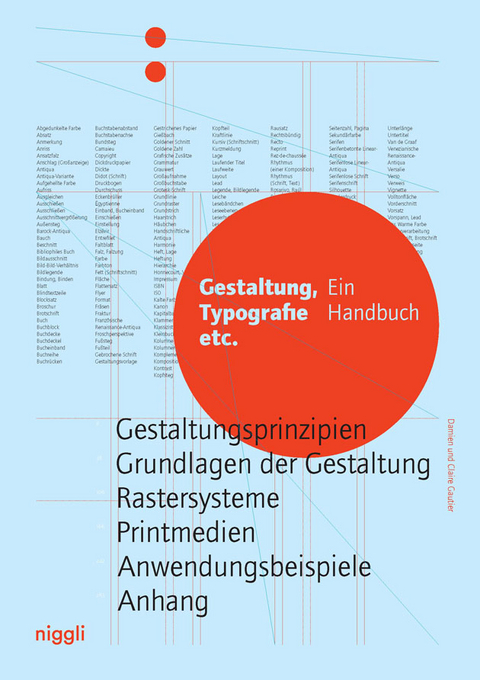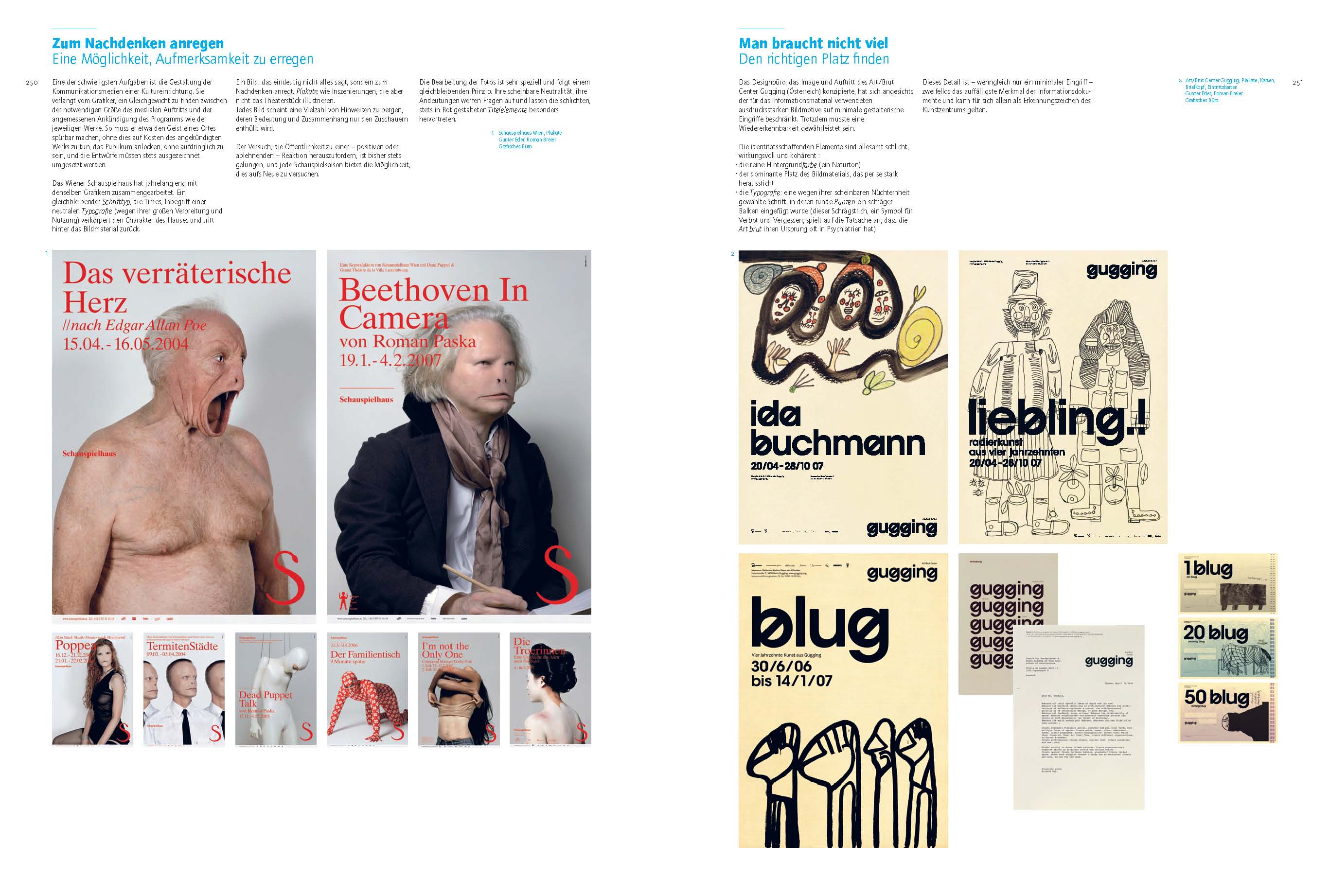
Gestaltung, Typografie etc.
Ein Handbuch
Warum sieht eine Zeitung anders aus als eine Zeitschrift oder ein Buch? Welche Auswirkungen hat die Verwendung einer bestimmten Schrift, welche die eines bestimmten Rasters? Und warum wirkt das eine Layout ausgesprochen passend und überzeugt und ein anderes eindeutig falsch?
Mittels Abbildungen, Zeichnungen und erläuternden Texten werden in diesem umfassenden Handbuch und Nachschlagewerk sämtliche Grundlagen und Fachbegriffe erklärt, deren Kenntnis an der Schnittstelle von Gestaltung und Produktion von Printmedien unumgänglich ist. Vom Aufbau einer Seite über die richtige Verwendung von Farben und Schriften bis hin zu Spaltenbreite und Zeilenlauf: Reich bebildert und mit zahlreichen Beispielen internationaler Druckerzeugnisse behandelt "Gestaltung, Typografie etc." sämtliche Aspekte guter Buch-, Plakat- und Anzeigengestaltung.
Damien Gautier (*1971) studierte Typografie am Atelier de création typographique in der Pariser École Estienne. Er ist Grafikdesigner, Typografie-Dozent und Mitbegründer der Multimedia-Agentur Trafik. 2001 erschien sein erstes Buch Typographie, guide pratique. Claire Gautier ist Dozentin an der École La Martinière-Diderot in Lyon. Als Malerin unterrichtet sie seit mehreren Jahren Grafikdesign- und Innenarchitektur-Studenten in Bildender Kunst.